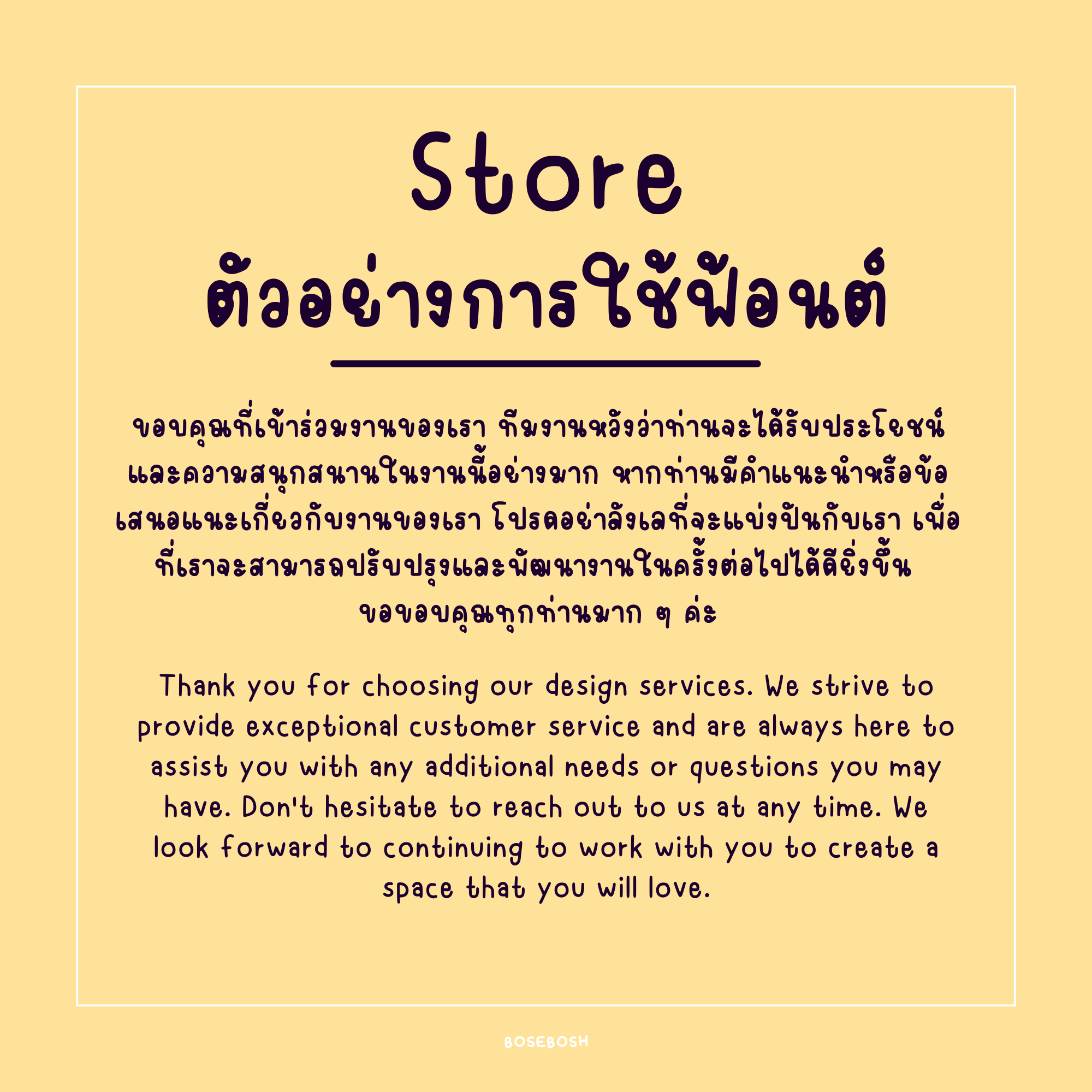
Store Font
✏️ Store — ฟอนต์ลายมือหนานิด ๆ เส้นคมชัด ตัวใหญ่กำลังดี เห็นชัดบนทุกพื้นหลัง
🎯 รองรับไทย อังกฤษ ตัวเลข วางสระพอดี ไม่มีเบี้ยว
💡 เหมาะกับชื่อร้าน, ป้ายประกาศ, หัวข้อโพสต์ หรือคำโปรยแนวขี้เล่นบนโซเชียล
🎀 ไม่ว่าจะใช้จดโน้ต เขียนสรุป ทำโปสเตอร์ ตกแต่งสไลด์ ทำปก หรือใส่ข้อความในวิดีโอ ก็ช่วยเพิ่มความสดใสได้ในทันที!
🖋️ ถูกออกแบบให้เหมือนลายมือจริง อ่านง่าย สบายตา
🔠 รองรับทั้งภาษาไทย ภาษาอังกฤษ ตัวเลขอารบิก และเลขไทย